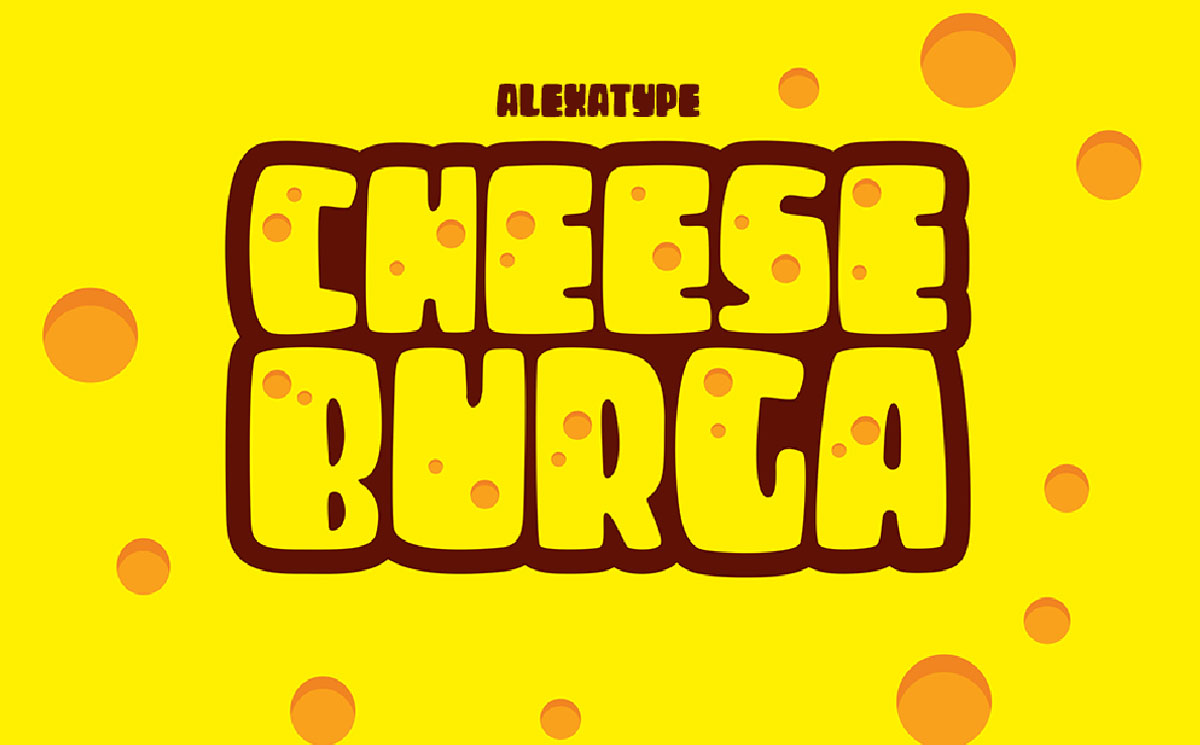
Font chữ cho chủ đồ đồ ăn Việt hóa SVN Cheeseburga | Phông chữ miễn phí
Trong ngành thiết kế đồ họa F&B (Food & Beverage), việc lựa chọn một phông chữ vừa thể hiện được tính chất thơm ngon, hấp dẫn của món ăn vừa đảm bảo chuẩn tiếng Việt là yếu tố vô cùng quan trọng. Font chữ cho chủ đề đồ ăn Việt hóa SVN Cheeseburga là sự kết hợp hoàn hảo giữa đường nét ngộ nghĩnh, dày dặn và năng động, giúp thương hiệu của bạn dễ dàng thu hút sự chú ý của khách hàng ngay từ cái nhìn đầu tiên. Đây là phông chữ miễn phí lý tưởng dành cho các nhà thiết kế, chủ quán ăn, cửa hàng trà sữa hay các chiến dịch marketing ẩm thực độc đáo.
Font Chữ Cho Chủ Đề Đồ Ăn Việt Hóa SVN Cheeseburga – Phông Chữ Miễn Phí Độc Đáo Cho Thiết Kế Ẩm Thực
Hình ảnh thương hiệu trong ngành dịch vụ ăn uống không chỉ dừng lại ở những bức ảnh món ăn chụp nét căng hay màu sắc bắt mắt, mà font chữ được sử dụng trên thiết kế cũng đóng vai trò quyết định cảm xúc của người xem. Một phông chữ quá cứng nhắc sẽ làm mất đi tính gần gũi, trong khi phông chữ quá mỏng lại khó gây ấn tượng thị giác mạnh mẽ. Đó chính là lý do font chữ cho chủ đề đồ ăn Việt hóa SVN Cheeseburga ra đời và trở thành công cụ đắc lực cho cộng đồng designer.
SVN Cheeseburga sở hữu phong cách Display Font với các đường nét bo tròn mềm mại nhưng vô cùng mập mạp, gợi liên tưởng trực tiếp đến những chiếc bánh burger béo ngậy, những ly trà sữa ngọt ngào hay các món ăn đường phố đầy hấp dẫn. Được việt hóa chỉn chu bởi đội nhóm SVN, phông chữ này giúp bạn tự do sáng tạo nội dung tiếng Việt mà không bao giờ lo lắng về lỗi font hay thiếu dấu câu.
1. Phong Cách Thiết Kế Béo Ngậy, Bo Tròn Đầy Năng Lượng
Điểm đặc trưng lớn nhất của SVN Cheeseburga nằm ở cấu trúc hình học của các ký tự. Mỗi chữ cái đều được thiết kế với độ dày (stroke weight) lớn, các góc được bo tròn mềm mại tạo cảm giác thân thiện, vui tươi và tràn đầy sức sống. Nét vẽ mập mạp này cực kỳ phù hợp với các thương hiệu đồ ăn nhanh, tiệm bánh, quán ăn vặt hay đồ uống giải khát.
Sự mũm mĩm trong từng nét chữ không chỉ tạo cảm giác ngon miệng mà còn đem lại hiệu ứng thị giác mạnh mẽ, giúp tiêu đề của bạn nổi bật hoàn toàn trên nền hình ảnh phức tạp. Dù bạn sử dụng trên phông nền tối hay sáng, SVN Cheeseburga vẫn giữ được vẻ cá tính và nổi bật không thể trộn lẫn.
2. Tối Ưu Hóa Việt Hóa 100% Chuẩn Xác Cho Tiếng Việt
Một trong những rào cản lớn nhất khi các nhà thiết kế Việt Nam sử dụng các phông chữ nước ngoài là lỗi hiển thị ký tự có dấu. Nhận thức được điều này, bản Việt hóa SVN Cheeseburga đã được tinh chỉnh tỉ mỉ từng dấu thanh (sắc, huyền, hỏi, ngã, nặng) cũng như các ký tự đặc trưng như ê, ơ, ư, đ.
Các dấu câu trong bản Việt hóa được thiết kế đồng điệu về độ dày và tỷ lệ so với thân chữ chính, giúp tổng thể dòng văn bản luôn cân đối, hài hòa. Bạn có thể yên tâm gõ các tiêu đề tiếng Việt dài mà không sợ bị lệch dấu, mất nét hay sai quy chuẩn thẩm mỹ.
3. Ứng Dụng Đa Năng Trên Nhiều Loại Ấn Phẩm Thiết Kế F&B
Font chữ SVN Cheeseburga không chỉ giới hạn trong một loại hình thiết kế duy nhất mà có khả năng biến hóa linh hoạt trên nhiều chất liệu và nền tảng khác nhau. Nhờ sự độc đáo trong tạo hình, phông chữ này đáp ứng tốt hầu hết các nhu cầu truyền thông của ngành ẩm thực:
• Thiết kế Menu (Thực đơn): Tạo điểm nhấn cho tên món ăn chính, món “best-seller” hoặc các chương trình khuyến mãi đặc biệt.
• Bao bì và Nhãn mác: In ấn lên ly giấy, túi takeaway, hộp đựng bánh, tem dán sản phẩm tạo phong cách trẻ trung, hiện đại.
• Poster và Banner Quảng Cáo: Làm nổi bật thông điệp truyền thông trên các kênh Social Media như Facebook, Instagram, TikTok hay các biển hiệu ngoài trời.
• Biển hiệu Cửa hàng: Tạo dựng nhận diện thương hiệu ngộ nghĩnh, thu hút khách hàng trẻ tuổi và giới học sinh, sinh viên.
4. Hiển Thị Nổi Bật Và Dễ Đọc Ở Mọi Kích Thước
Bên cạnh yếu tố nghệ thuật, tính dễ đọc (legibility) luôn là ưu tiên hàng đầu của một font chữ thiết kế tiêu đề. SVN Cheeseburga đáp ứng hoàn hảo tiêu chí này nhờ tỷ lệ khoảng cách giữa các chữ cái được tính toán hợp lý. Ngay cả khi thu nhỏ để làm logo góc áo hay phóng to trên bảng hiệu hàng chục mét, người xem vẫn có thể đọc rõ từng chữ một cách dễ dàng.</p>
Khả năng hiển thị xuất sắc trên cả màn hình kỹ thuật số (độ phân giải cao lẫn thấp) và bản in thực tế giúp SVN Cheeseburga trở thành lựa chọn an toàn nhưng không kém phần phá cách cho mọi dự án F&B.
Hướng Dẫn Phối Màu Và Sử Dụng Font SVN Cheeseburga Hiệu Quả